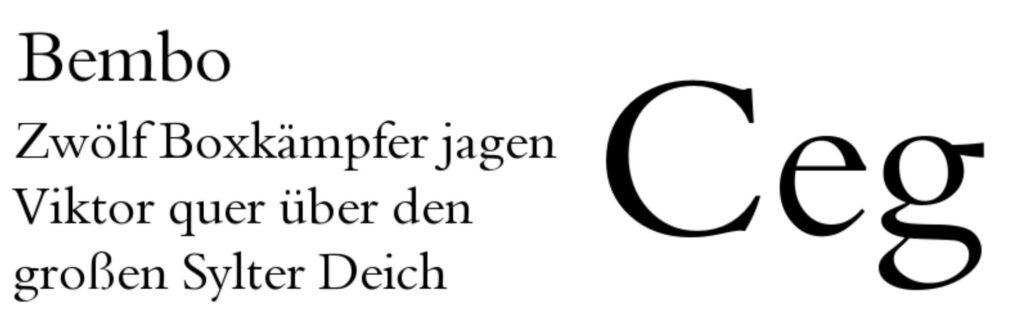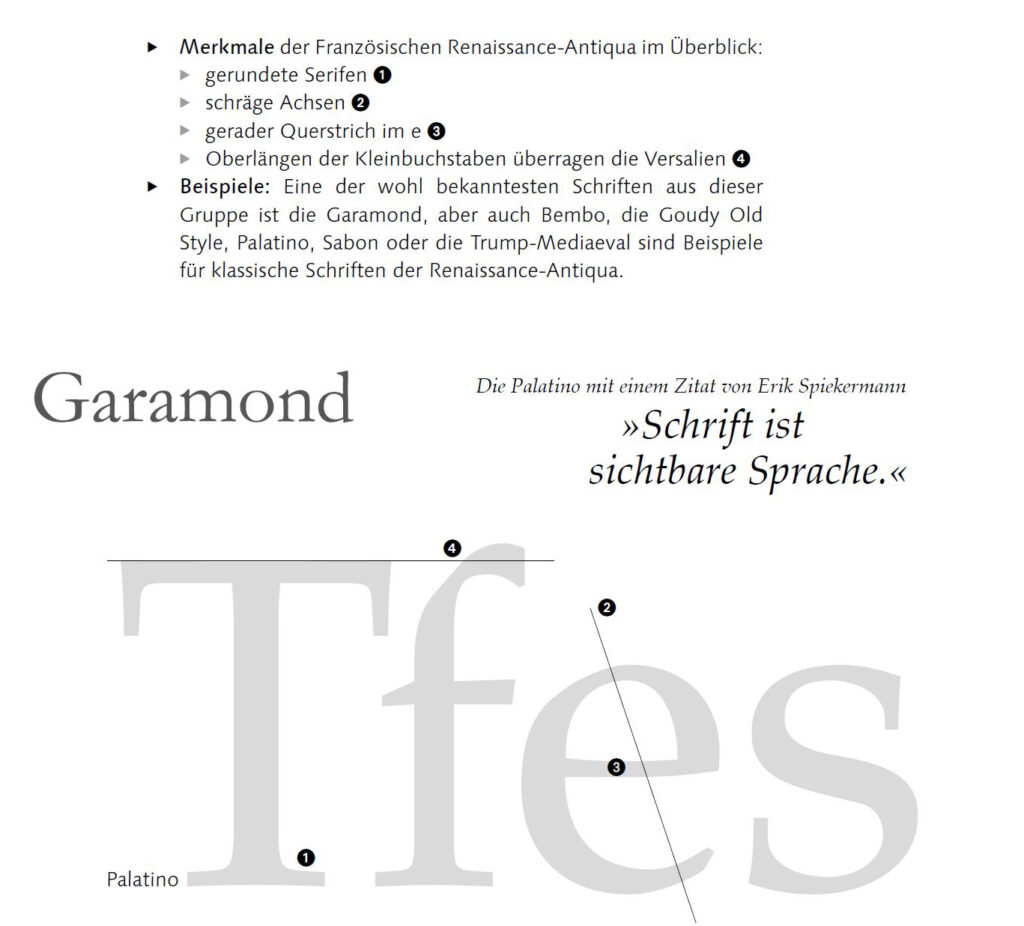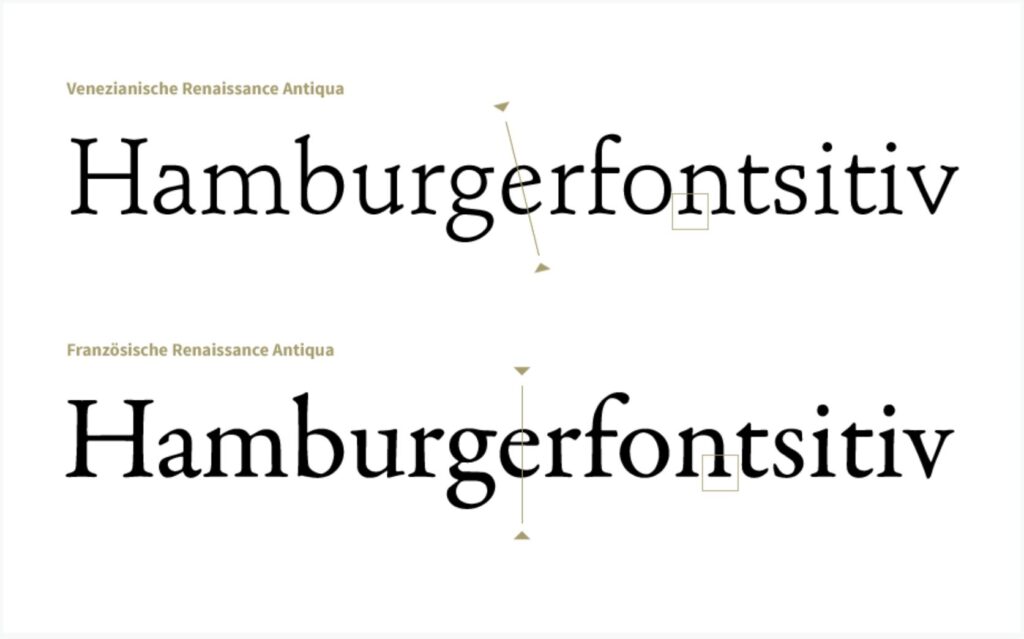
Französische Renaissance-Antiqua
Entstanden Mitte des 16. Jahrhunderts, geprägt von Claude Garamond. Großbuchstaben orientieren sich an der Capitalis Quadrata, Kleinbuchstaben an der karolingischen Minuskel. Unterschiede zur venezianischen Form: Achsen tendieren stärker zur Senkrechten, Serifen wirken kantiger, Kontraste deutlicher.
• Strichstärken: leicht stärker als venezianische Antiqua, moderater Kontrast
• Serifen: feiner, spitzer, präzise geformt
• Achsen: tendieren mehr zur Senkrechten → strengeres Schriftbild
• Proportionen: ausgeglichene Ober- und Mittellängen, harmonische Lesbarkeit
• Gestaltung: klar, elegant, nüchterner als Venezianisch
• Wirkung: seriös, kultiviert, gut für Bücher und Drucktexte geeignet